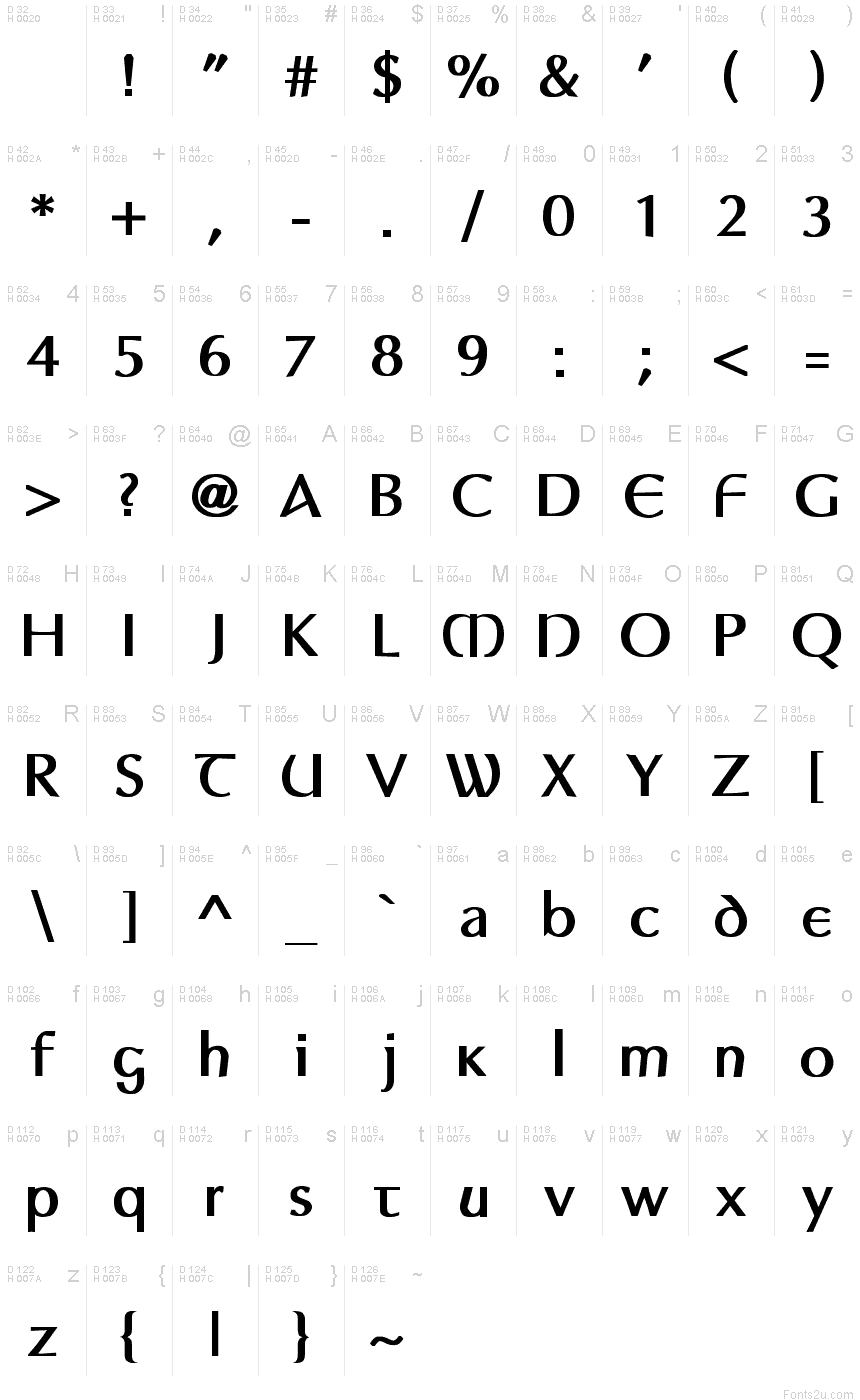
<p>Auptimagh AH od Andreasa Höfelda to darmowy krój pisma typu display w stylu retro, o ostrym i literackim charakterze. Wąski rytm, wyraziste krzywizny i elegancja dawnego druku nadają nagłówkom teatralnego sznytu – to nie jest zakurzona nostalgia, lecz raczej efekt świeżego odbicia farby na fakturowanym papierze.</p>
<p>Auptimagh AH świetnie sprawdza się na plakatach vintage, okładkach niezależnych książek, okładkach albumów, w menu kawiarnianych, na opakowaniach butikowych, w nagłówkach redakcyjnych i ulotkach. Stosuj go w większych rozmiarach i zestaw ten darmowy font ze spokojnym, bezszeryfowym krojem w tekście głównym, aby jego ekscentryczna sylwetka pozostała wyrazista.</p>
Auptimagh AH